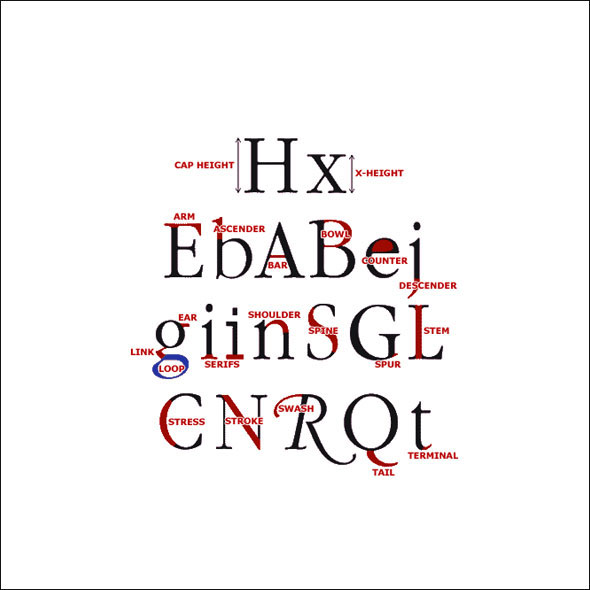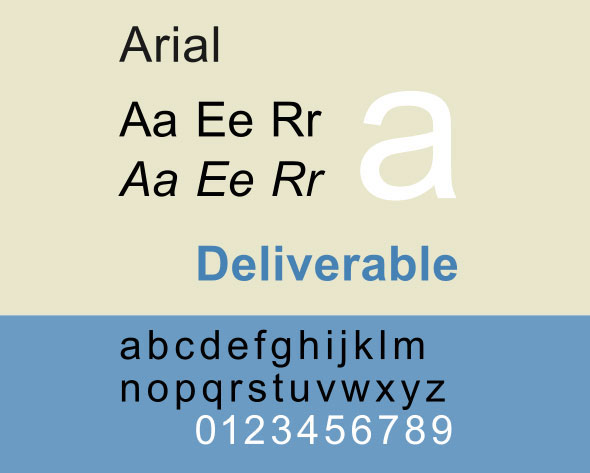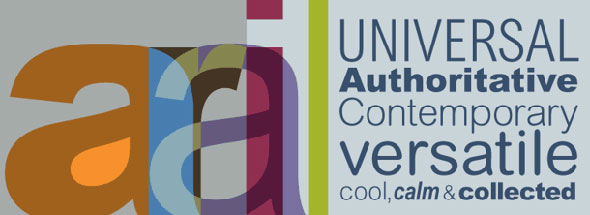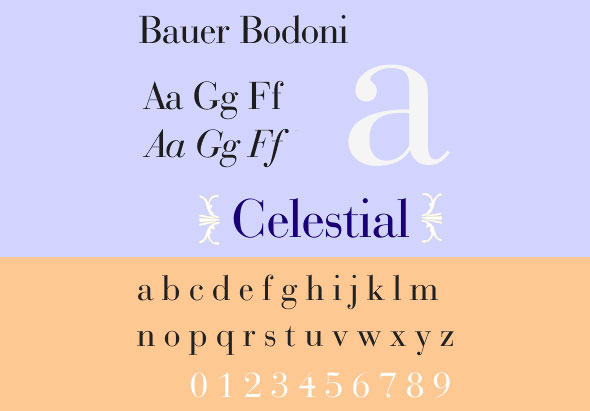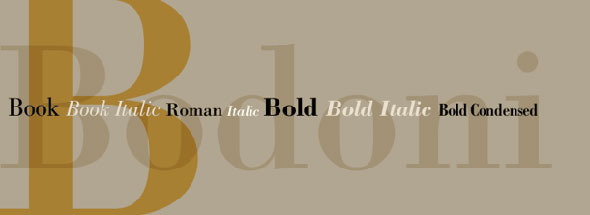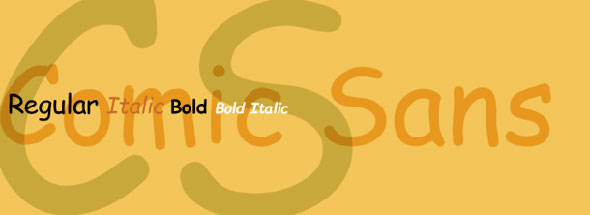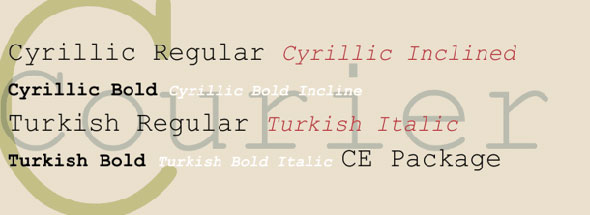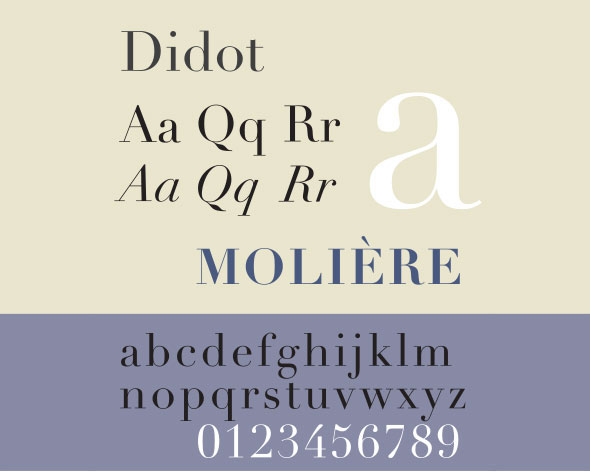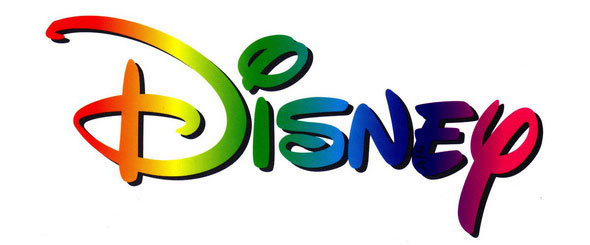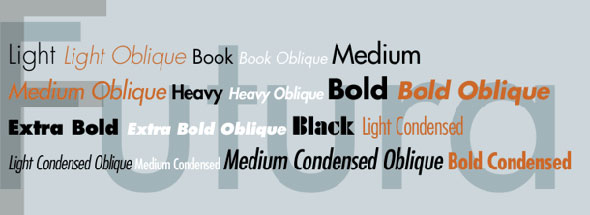
Психология восприятия шрифта и ее практическое применение
Психология шрифта определяет какой именно эффект произведет тот или иной шрифт на пользователя. Типографика или шрифты — очень значимая составляющая, игнорирование которой приводит к созданию менее качественного веб-дизайна. Многие дизайнеры фокусируют внимание на красоте и художественной привлекательности проекта, цветовых сочетаниях и практическом значении, но немногие относятся с той же щепетильностью к шрифтам. Они просто не понимают, что именно гарнитура передает пользователю посыл.
Шрифт — один из элементов, к которым нужно относиться очень серьезно. Шрифты обеспечивают читабельность и несут главный смысл. Психология шрифта играет роль позвоночника в эффективности веб-дизайна. Каждый дизайнер знает, что цвета влияют на настроение, эмоции и чувства людей. Шрифты в этом смысле дают тот же эффект что и цвета.
Веб-разработчикам и дизайнерам доступны тысячи шрифтов. Выбор их стиля может показаться случайным решением, однако знание психологии шрифта сделает ваш выбор осознанным. Есть два основных типа шрифтов:
1. С засечками: шрифты с короткими штрихами на нижней и верхней части букв.
2. Без засечек: шрифты без штрихов.
Оба типа шрифтов действуют по-разному на пользователей. Изучение графики включает в себя психологию шрифта. В этой статье вы узнаете о психологическом влиянии шрифтов и о принципах выбора шрифта. Определенное начертание несет определенный смысл и играет важную роль в функциональности дизайна: к примеру, если создаете сайт для классического, традиционного бизнеса, стоит выбрать шрифт с засечками; если вы хотите подчеркнуть современность и уникальность бизнеса, выбирайте шрифт без засечек.
Психология шрифта
Inspiration Lab создали одну из лучший схем по выбору шрифта.
Выбор шрифта зависит от его эстетической ценности, однако это гораздо сложнее, чем кажется. Типографика играет жизненно важную роль в пользовательском интерфейсе, а пользователь тратит больше времени на текст, чем на картинки или видео. Все параметры шрифта, такие как расстояние между буквами, цвет и размер оказывают определенное влияние на посетителей. Именно поэтому типографика считается основным элементом в конструкции. Давайте перечислим психологические типы шрифтов, чтобы понять их влияние на человека. Ниже перечислены типы психологического воздействия шрифтов.
Визуальная риторика текста
Риторика — это наука о использовании речи эффективно и убедительно. Визуальная риторика включает в себя все впечатление от документа. Визуальные элементы создают свои собственные смысловые цепочки, дающие более полную детализацию представленного материала.
Семантическая память в психологии шрифта
Семантическая (смысловая) память создает информацию о конкретной вещи и сохраняет память о ней. Когда вы смотрите на шрифт, который видели прежде, ваша семантическая память генерирует тот же эффект, которые шрифт произвел на вас ранее.
Общее типографическое направление
Исследования показывают, что эмоциональное состояние пользователя является результатом его опыта взаимодействия с дизайном. Шрифты способны влиять на внешний вид документа, и различные гарнитуры, оказывающие различное эмоциональное воздействие на читателя, стоит выбирать очень внимательно. Неправильный выбор типа шрифта может вызвать у посетителя негативные эмоции.
Советы по улучшению типографики
• Межстрочный интервал
Один из самых важных элементов, обеспечивающих комфортное чтения — межстрочный интервал. Наиболее удобным для глаз читателя считается значение — 30-60% от размера вашего шрифта. Если вы выбрали размер шрифта в 12px, размер вашего межстрочника должен составлять 4-6px, чтобы текст читался легко.
• Длина строки
Постарайтесь сделать ваши строки короткими. Их удлинение снижает интерес пользователя. Оптимальная длина строки составляет от 45 до 65, это примерно от 7 до 10 слов.
• Пробелы
Пробелы в документе являются одним из важнейших составляющих ui. Если пробелы достаточно широки, то читатель сможет читать текст без усталости и усилий.
• Вертикальный ритм
В документе должен быть логический потом от заголовка к содержанию. Это создает ритм и делает документ привлекательнее для читателя.
• Вертикальная иерархия
Вертикальная иерархия мягко проводит читателя по документу от первого заголовка до последнего. Концепция заключается в повышении читабельности и представлении содержания документа в удобном для читателя формате.
• Индивидуальность
Психология типографики предполагает понимание индивидуальности шрифта. Индивидуальность начертания определяется видом и содержанием. Например, шрифт Times используется в документе о приеме на работу, чтобы сделать его более традиционным и официальным; а Verdana используется для чего-то современного и менее официального.
Не со всем согласна. Гельветика, футура и готам — гротески.
=-O Не уверен, что при размере шрифта 12рх межстрочное 4-6рх будет вообще читабельно. Наверняка автор имел в виду НА 30-60% больше, а перевели, что перевели. Поправьте.
Шрифты без засечек и брусковые шрифты проиллюстрированы одной и той же картинкой =/